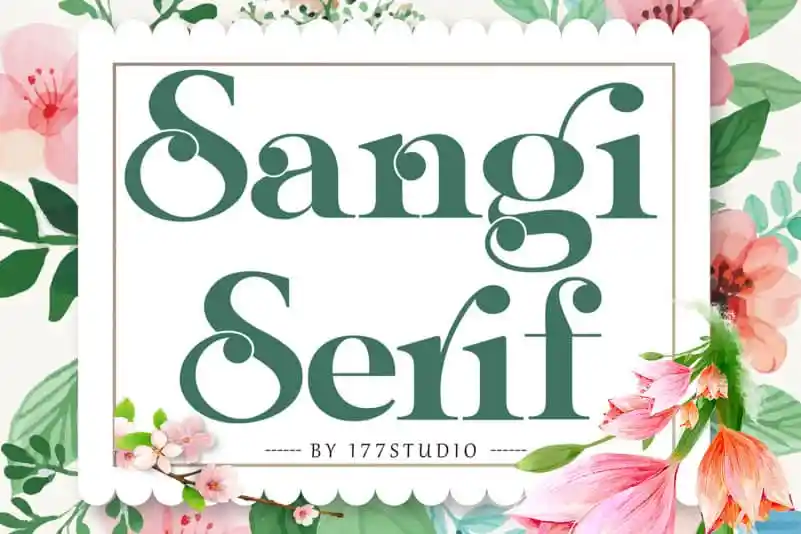
Sangi Serif é uma fonte serif com curvas equilibradas para uso no ambiente criativo do Brasil. Essa fonte abrange caracteres maiúsculos e minúsculos, proporcionando um visual agradável e sofisticado ideal para projetos de design variados. Suas alternativas estilísticas oferecem uma ampla gama de opções, permitindo que designers criem designs diversos e inovadores, desde logomarcas em t-shirts até postais e cartazes. Ideal tanto para headlines quanto para logotipos, anúncios, embalagens e materiais publicitários, Sangi Serif é uma fonte de qualidade perfeita para o design gráfico brasileiro.